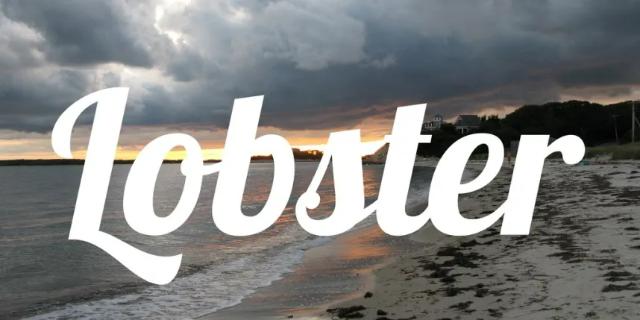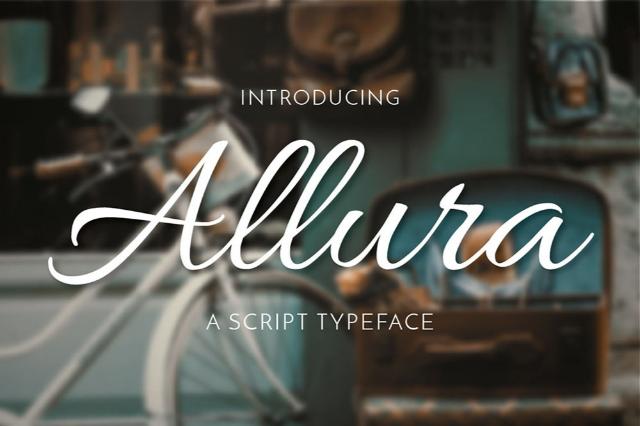
Trong thiết kế website và sáng tạo nội dung, typography không chỉ đơn thuần là những chữ cái vô tri. Đặc biệt đối với các thẻ Heading (H1, H2, H3), font chữ chính là “linh hồn” định hình phong cách thương hiệu và quyết định trải nghiệm người dùng. Bài viết này sẽ cung cấp cho bạn tư duy lựa chọn và cách tối ưu font chữ tiêu đề đẹp, Việt hóa hoàn chỉnh, đáp ứng cả tiêu chuẩn thẩm mỹ lẫn kỹ thuật SEO khắt khe nhất năm 2026.
1. Tại sao việc chọn font chữ tiêu đề (Heading) lại quan trọng?
Việc chọn lựa đúng font chữ cho các tiêu đề lớn mang lại những giá trị cốt lõi vượt xa yếu tố thẩm mỹ thông thường:
- Tác động thị giác đầu tiên (Quy tắc 3 giây): Khách truy cập trực tuyến thường cực kỳ thiếu kiên nhẫn. Một tiêu đề H1 sử dụng font chữ sắc nét, nổi bật sẽ thu hút ánh nhìn và giữ chân người dùng ngay trong 3 giây đầu tiên, quyết định việc họ có tiếp tục cuộn xuống để đọc bài viết hay thoát trang.
- Định hình nhận diện thương hiệu: Sự nhất quán trong việc sử dụng typography giúp khắc sâu hình ảnh doanh nghiệp vào tâm trí khách hàng. Một phòng tranh nghệ thuật không thể dùng chung font chữ với một công ty xây dựng; sự lựa chọn phải đồng điệu tuyệt đối với thông điệp và tệp khách hàng mục tiêu.
- Tối ưu hóa UI/UX và chỉ số SEO: Tiêu đề rõ ràng, kích thước chuẩn giúp cải thiện mức độ dễ đọc (readability) trên mọi thiết bị di động. Trải nghiệm đọc tốt sẽ kéo dài thời gian On-site, giảm tỷ lệ thoát (Bounce Rate) – những tín hiệu tích cực mà Google đánh giá rất cao để xếp hạng website.
Top 20 Font chữ tiêu đề đẹp nhất đa ngành nghề
Dựa trên quá trình phân tích ý định tìm kiếm và nhu cầu thực tế của người dùng, dưới đây là danh sách 20 font chữ tiêu đề đẹp nhất, được phân loại chi tiết theo 4 nhóm ngữ cảnh sử dụng. Hãy cùng khám phá để chọn ra “vũ khí thị giác” tối ưu nhất cho dự án tiếp theo của bạn.
Nhóm 1: Font tiêu đề chuyên nghiệp, thanh lịch (Dành cho Word, Báo cáo, Slide)
Trong môi trường doanh nghiệp hay học thuật, sự rõ ràng, hiện đại và đáng tin cậy là yếu tố kiên quyết. Nhóm font chữ dưới đây sẽ giúp các báo cáo, bản thuyết trình hay tài liệu nội bộ của bạn thoát khỏi vẻ nhàm chán của các font mặc định.
- Montserrat
Được mệnh danh là lựa chọn “quốc dân” cho thiết kế phẳng hiện đại, Montserrat sở hữu nét chữ không chân (Sans-serif) hình học, mượt mà và vô cùng chuyên nghiệp. Font chữ này có không gian thở (kerning) tuyệt vời, khiến nó trở thành lựa chọn số 1 cho các tiêu đề slide PowerPoint và báo cáo tài chính cần sự minh bạch, dứt khoát.
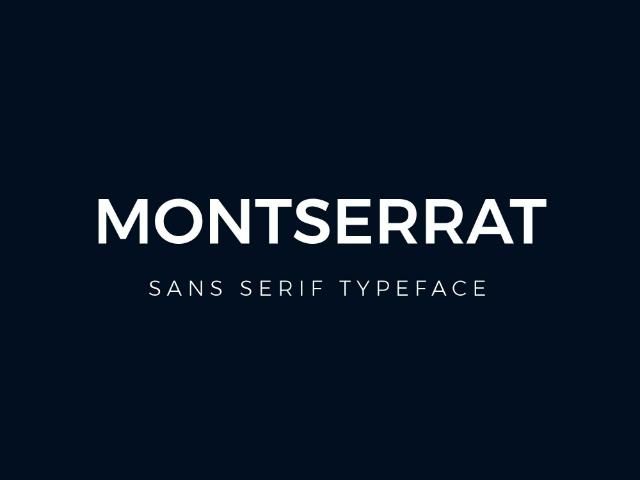
- Playfair Display
Nếu bạn cần một chút quyền lực và sự sang trọng, Playfair Display là một kiệt tác. Đây là font có chân (Serif) mang nét cổ điển với độ tương phản cao giữa nét thanh và nét đậm. Cảm giác tin cậy, quý phái mà font chữ này mang lại cực kỳ phù hợp cho bìa sách, tạp chí, catalogue sản phẩm cao cấp hay các báo cáo thường niên của doanh nghiệp.
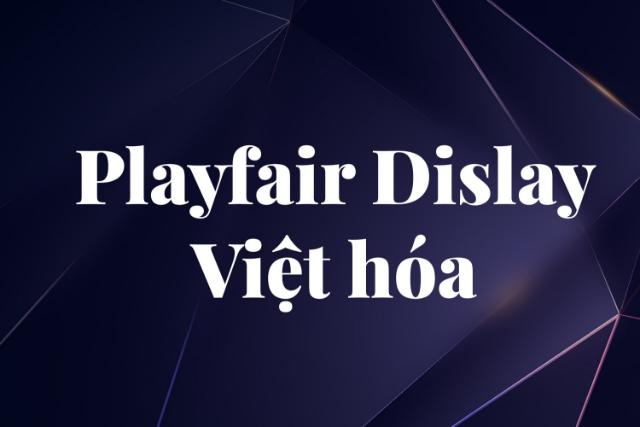
- Roboto
Không cần quá phô trương, Roboto ghi điểm tuyệt đối nhờ sự đơn giản, thân thiện và khả năng tối ưu hóa hiển thị trên mọi kích thước màn hình. Nếu bạn có một tiêu đề dài hoặc cấu trúc báo cáo nhiều cấp độ, Roboto sẽ giúp nội dung trở nên ngăn nắp và cực kỳ dễ đọc.
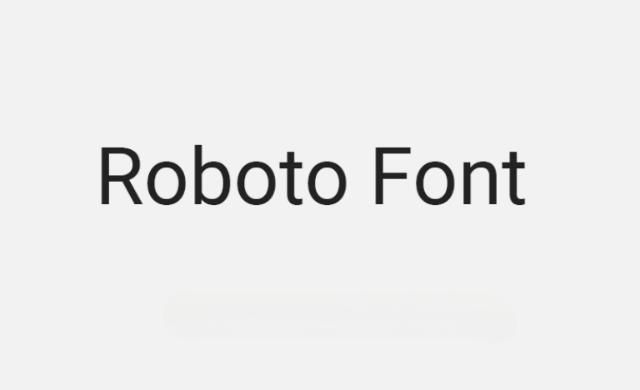
- Lora
Lora là đại diện xuất sắc của dòng font Serif đương đại. Với độ tương phản nét thanh nét đậm được tinh chỉnh hoàn hảo, Lora mang lại vẻ đẹp đậm tính nghệ thuật nhưng không làm mất đi tính khuôn thước. Đây là lựa chọn tuyệt vời cho các bài tiểu luận, tài liệu nhân sự hoặc các báo cáo mang tính văn hóa, nghệ thuật.
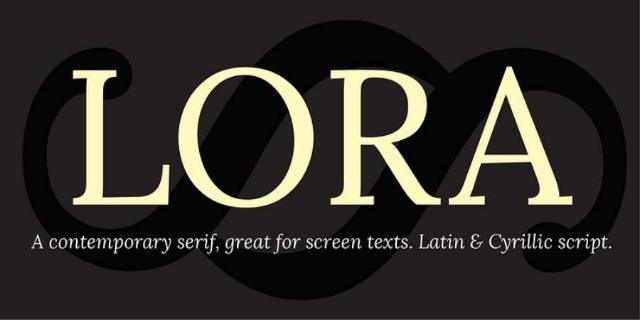
- Open Sans
Mang phong cách trung lập và an toàn, Open Sans giúp tiêu đề của bạn dễ dàng nổi bật mà không tạo cảm giác lấn át hay phô trương. Cấu trúc chữ mở rộng của Open Sans giúp người đọc lướt qua thông tin một cách trơn tru phù hợp cho mọi loại tài liệu từ Word đến các giao diện Web nội bộ.
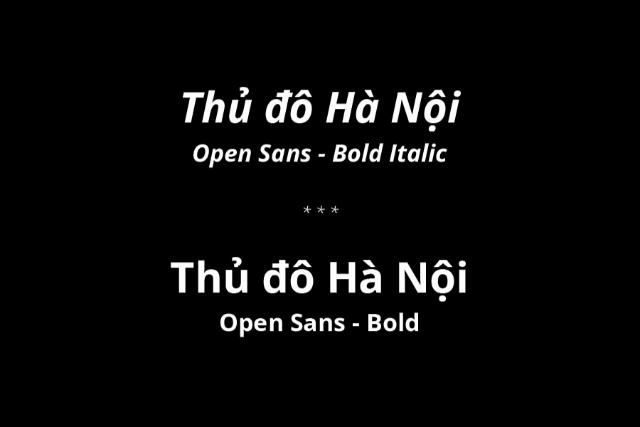
Nhóm 2: Font tiêu đề nghệ thuật, mềm mại (Calligraphy / Pinterest Style)
Khi thiết kế của bạn hướng tới phong cách sống (lifestyle), F&B, hay các sự kiện cá nhân, cảm xúc là yếu tố dẫn dắt. Nhóm font mang phong cách Calligraphy (Thư pháp/Viết tay) dưới đây sẽ thổi hồn vào từng con chữ.
- Pacifico
Mang nét cọ vẽ (brush) đặc trưng, Pacifico toát lên sự vui tươi, thoải mái và tràn đầy năng lượng. Font chữ này là “chân ái” cho các tiêu đề thiết kế liên quan đến du lịch, menu quán cafe, hoặc các bài blog lifestyle hướng tới giới trẻ.
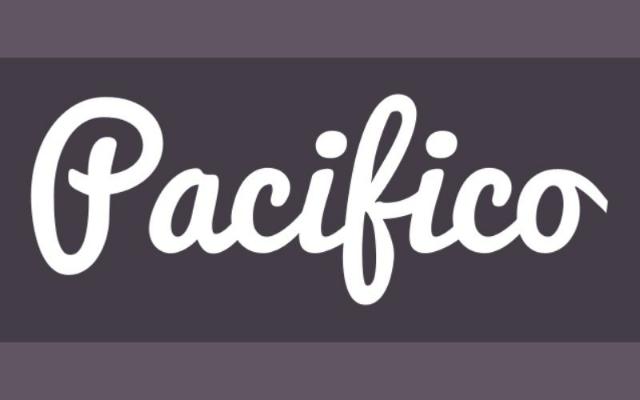
- Great Vibes
Đúng như tên gọi, Great Vibes mang đến những “rung cảm tuyệt vời” thông qua nét chữ thư pháp viết tay thanh lịch, uốn lượn và vô cùng tinh tế. Đây là sự lựa chọn không thể thay thế cho thiệp cưới, sự kiện vinh danh sang trọng hoặc các tiêu đề hình ảnh mang tính lãng mạn.
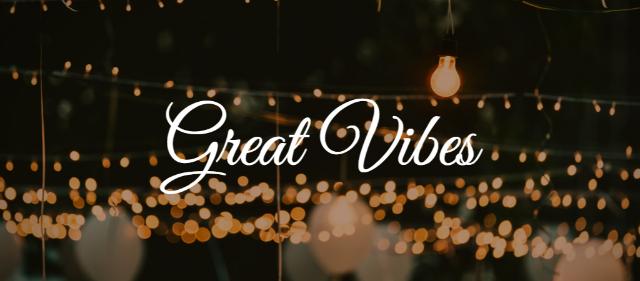
- Dancing Script
Nếu Great Vibes mang nét trang trọng thì Dancing Script lại đem đến sự tự do. Với độ nghiêng tự nhiên và kích thước chữ không đồng đều có chủ ý, Dancing Script tạo ra cảm giác thân thiện, năng động và mang đậm tính cá nhân hóa (Personalization) cho thiết kế.
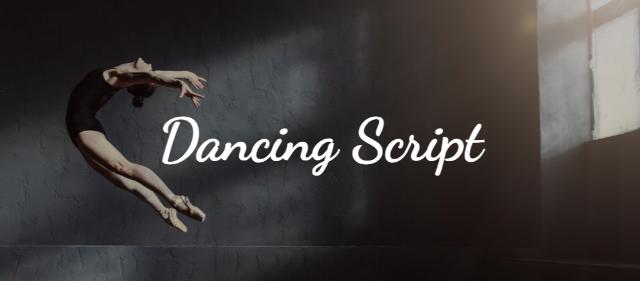
Font chữ tiêu đề đẹp không chỉ giúp thiết kế nổi bật mà còn quyết định cách người đọc cảm nhận nội dung ngay từ cái nhìn đầu tiên. Chọn đúng font, dùng đúng ngữ cảnh và giữ sự dễ đọc sẽ giúp tiêu đề vừa thu hút, vừa chuyên nghiệp, vừa truyền tải thông điệp rõ ràng hơn.